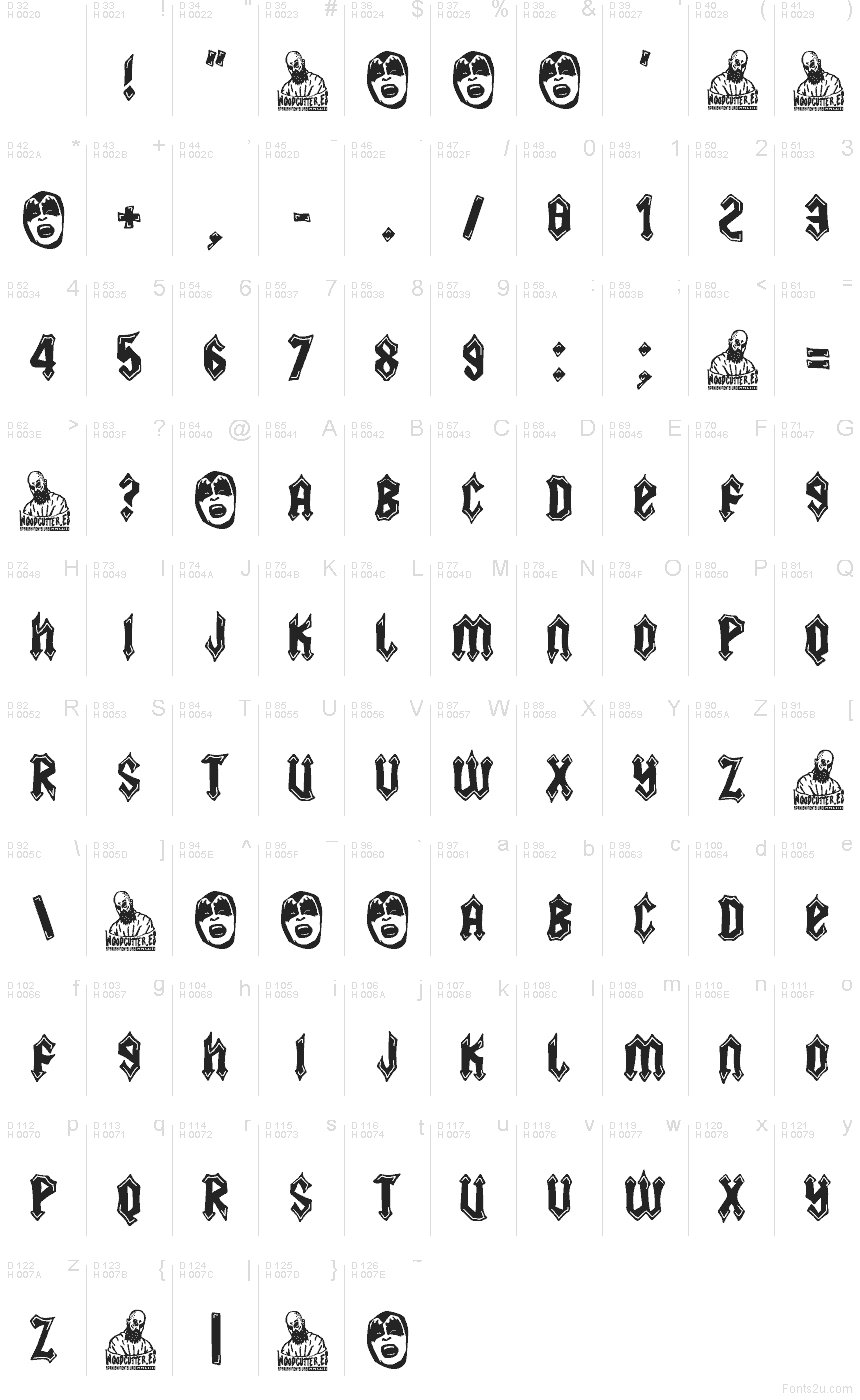
Metal Empire
Písmo Metal Empire od Woodcutter Manero je bezplatný gotický font s ostrými tvarmi blackletter, špicatými oblúkmi a hranatými rezmi, ktoré písmenám dodávajú vytesaný, metalom inšpirovaný rytmus. Znaky pôsobia kompaktne a vzpriamene, s úzkymi krivkami a tvrdými, zlomenými spojmi, vďaka čomu písmo nepôsobí príliš zdobene alebo mäkko.
Metal Empire je bezplatný font vhodný pre logá kapiel, nadpisy plagátov, obaly albumov, hernú grafiku, návrhy tetovaní a branding v temnom štýle, kde starosvetská štruktúra vyžaduje drsnejšiu hranu. Jeho špicatá geometria sa skvele hodí aj na letáky, etikety a dekoratívne nadpisy, ktoré potrebujú gotický tón bez zbytočných ozdôb.